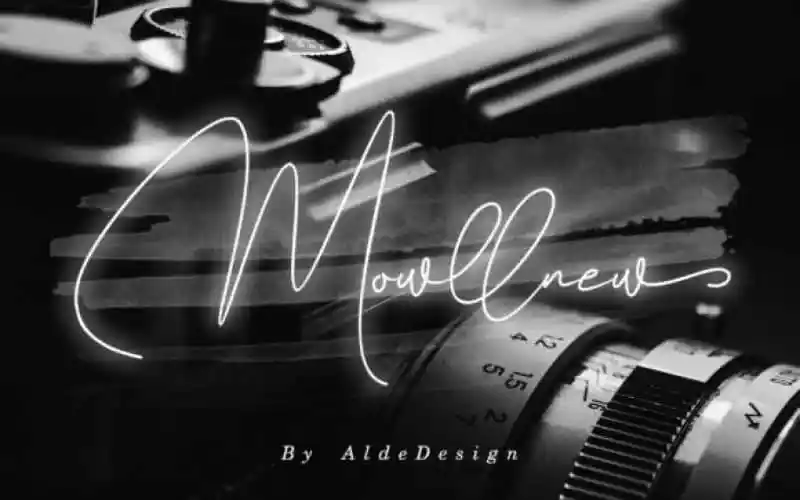
Mowllnew Handwritten Font – Download Grátis
A Mowllnew Handwritten Font é uma fonte script monolínea criada por aldedesign, que dá ao estilo de escrita natural do Jakarta Signature uma aparência incrivelmente autêntica. Esta fonte oferece um toque diferenciado e único ideal para diversas aplicações, como logotipos, citações impressas em listradas, fitos, selos, embalagens, headlines, posters, camisetas e cartões de agradecimento para casamentos. Com seu design cuidadosamente elaborado, esta fonte é uma ótima escolha para aqueles que buscam estilizar suas criações com um toque autêntico e envolvente. Seja você um designer gráfico ou simplesmente alguém que aprecia belas fórmulas de texto, certamente irá adorar a Mowllnew Handwritten Font.